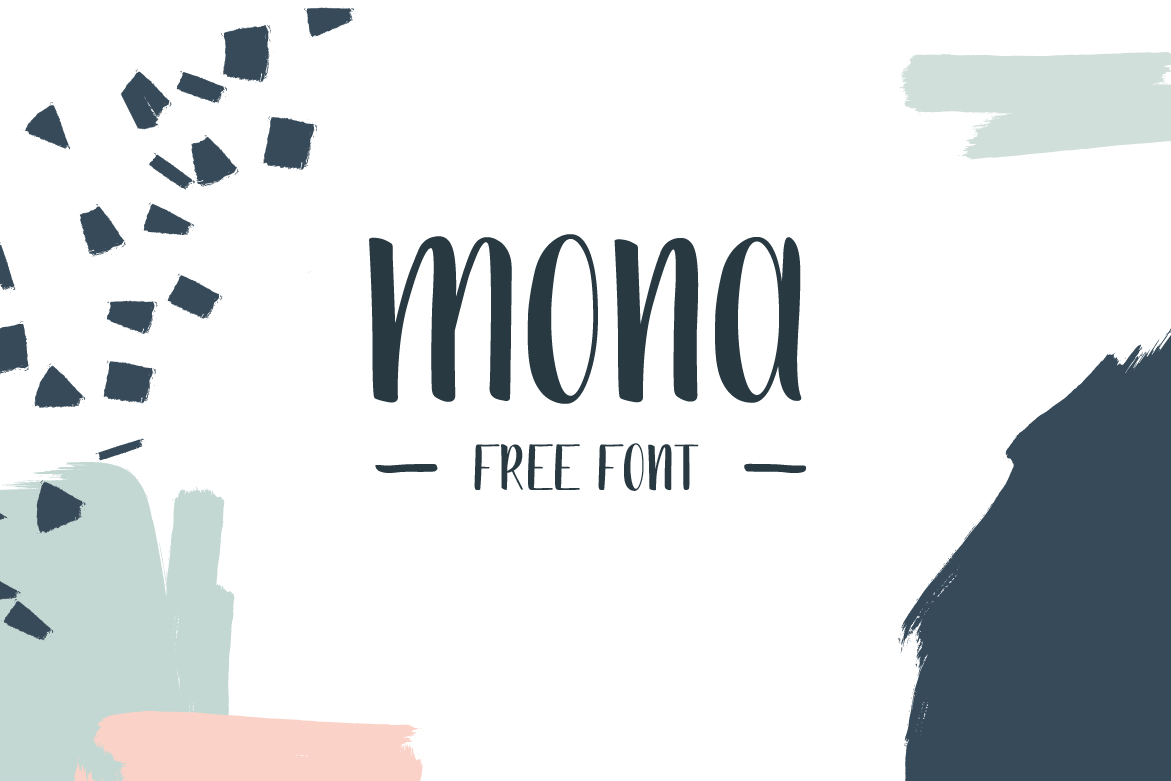
Mona Handdrawn Font – Download Grátis
A Mona Handdrawn Font é uma opção perfeita para quem procura algo único e envolvente para seu próximo projeto visual. Desenvolvida por Gatis Vilaks, esta fonte abrange linhas finas contrastantes com linhas grossas, proporcionando um estilo que se destaca em qualquer aplicação gráfica. Perfeito para criar identidades visuais, logos e design de embalagens, a Mona Handdrawn é uma excelente escolha para quem busca adicionar um toque autêntico e interessante à sua arte digital. Seu formato script oferece uma aparente naturalidade que traz um ar único e moderno ao seu trabalho, dando-lhe o poder de transformar ideias em realidade visuais. Este é mais do que apenas uma fonte; ele é uma ferramenta para expressar a sua personalidade visual de maneira única e impactante.
Designer: Gatis Vilaks